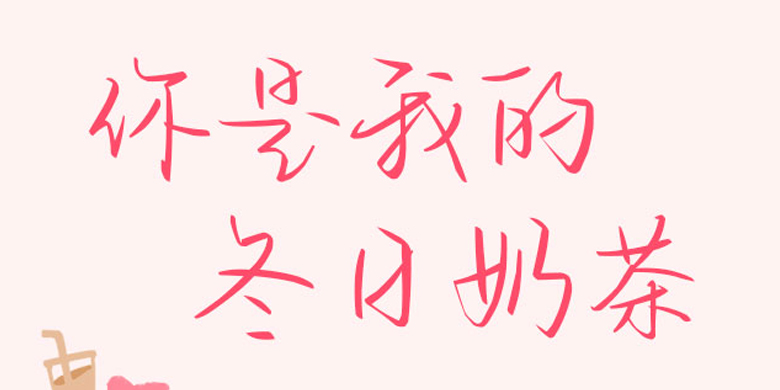
方正手迹-你是我的冬日奶茶
字体品牌: 方正手迹 设计师:刘殿儒 字体分类:创意书写 字体属性:精品字 字符集:简繁扩展(GBK) 发布时间: 2020
这款字连笔较多,笔画线条富于变化。近似日常书写的风格,看似随意,却有着既亲切又有行云流水般的写意书风。行笔劲健爽利,抑扬顿挫,富有韵律感。适用于文艺类的书刊、品牌广告和产品包装设计,以及社交网络的个性化用字。